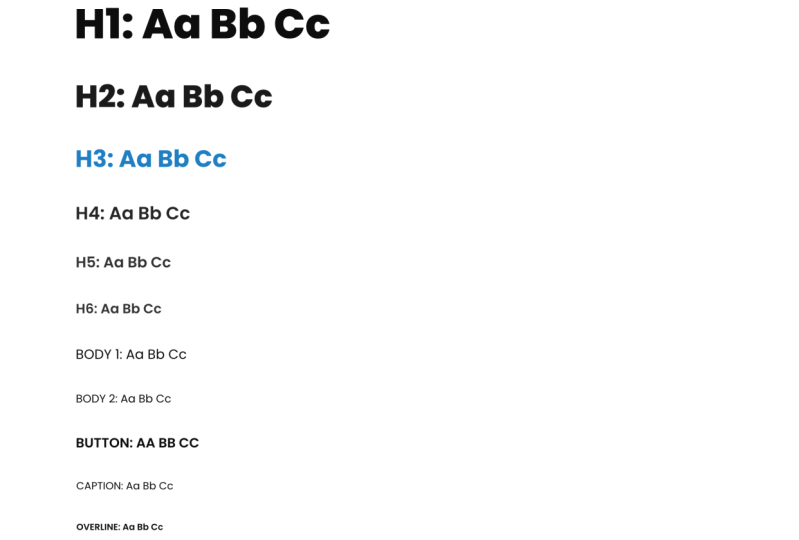
1. Introduction du cours: Les polices sont un élément crucial de chaque conception, car ce
sont elles qui
racontent l'histoire, guident l'utilisateur là où
il doit cliquer et où il doit aller
dans votre conception. Donc, choisir une bonne famille de polices et choisir une bonne famille de polices
pour les déchets est vraiment important et vraiment
une clé pour avoir un bon
et familles de polices, poids de police et
allons parler des différentes polices et familles de
polices. Quelle est la différence
entre eux ? Que sont les empattements et les sans empattement, différents poids de police
et comment les utiliser , les
différentes polices, échelles,
et comment les utiliser et créer votre propre bot pour choisir les
polices pour vos projets. Et enfin, comment associer des polices. Votre projet dépend de la complexité du projet
dans le sujet du projet, votre
projet de classe Skillshare consiste à créer une échelle de police à l'aide du
pour vous en tant que designer. Et cela profitera vraiment à vos utilisateurs, car cela
leur donnera plus de valeur. Ils vont
y rester plus longtemps parce que c'est une
expérience plus agréable pour eux. J'ai donc hâte de vous
voir dans ce cours et créons de
superbes combinaisons de polices.
2. Polices de polices VS: L'une des principales erreurs
que je vois de jeunes designers faire est d'appeler des polices, des polices caractères, ce qui
n'est pas vraiment vrai. Typeface est vraiment
une famille de polices. Et la police n'est qu'une variation au
sein de cette famille. Laissez-moi vous donner un bref exemple. Imaginez que vous utilisiez la police
Roboto par exemple. Et puis à l'intérieur de
l'autre fonte d'eau, vous avez Bolt, Regular,
Fine, Ultra Bold. Ce sont toutes des polices, mais le rapport lui-même est une police. La famille endettée est la principale
idée fausse des designers. Ils essaient de
pousser l'idée
que la police est primordiale
alors qu'elle ne l'est pas vraiment. Ce que vous pouvez avoir, c'est différents types de
variations de polices à l'intérieur de la même famille ou
une bouteille est vraiment un bon exemple car
vous avez Roboto regular, Roboto normal et puis vous avez quelque chose appelé roboto slab, qui est complètement une police de caractères, lignes
vraiment grasses, et il est
vraiment utilisé principalement pour l'impression, mais vous pouvez également l'utiliser dans
une sorte de conception Web audacieuse. Mais c'est là le
point essentiel. N'essayez pas de confondre polices
avec des familles de
polices, car les familles de
polices peuvent contenir plusieurs polices différentes. Et les polices ne sont que des variations au
sein de cette famille de polices. Comme je l'ai dit, il peut y avoir plusieurs polices
au sein d'une même famille. Alors gardez cela à l'esprit
et ne vous y trompez pas. Vous pouvez utiliser toute la famille ou police à l'intérieur de votre design, ou vous pouvez simplement utiliser
une variante telle que, disons dans cet exemple, Roboto regular ou Roboto bold. Nous allons y revenir dans quelques vidéos de ce cours. Mais je
voulais juste le souligner.
3. Types de polices: Souvent, lorsque j'
interviewe de jeunes designers
lorsque je leur parle, ils ne savent pas vraiment quelle est
la différence entre Serif et Sans Serif
en matière de police, c'est vraiment super simple. Et je suis allé de l'avant et j'ai trouvé
un très bon article. Je vais le lier dans le fichier de ressources de
la classe. Alors assurez-vous de le regarder et lire vous-même
car nous
n'allons pas l'approfondir trop
dans cette vidéo, mais je veux juste vous montrer
rapidement quelles sont les différences
entre les empattements, sans empattement, et lorsque
chacun d'entre eux est utilisé. Voici donc
cet article que j'ai
mentionné et qui provient d'Adobe.com, Creative Cloud Design Discover. Et je vais laisser
le lien vers cet article, comme je l'ai dit dans les fichiers de ressources de la
classe. Vous pouvez donc voir quelques
exemples ici. Peut-être que cela ne vous permet
pas de vous distinguer. Vous avez peut-être vu des polices comme celles-ci. Mais quelle est réellement
la différence entre Serif et Sans Serif ? Nous avons donc ici l'indice dans le nom et la principale
différence entre ces polices. Donc ces choses à la fin de
la lettre elle-même sont du surf. Et vous pouvez voir ici, nous n'avons pas
ce surf de sable, si je ne me trompe pas,
c'est français. Donc sans ces
empattements à la fin. C'est donc la principale différence entre les serfs et les serveurs d'envoi. Maintenant, quand vous pouvez les utiliser, vous pouvez voir quand
utiliser des polices avec empattement. Il va donc être
très détaillé savoir quand les utiliser
et comment les utiliser. Vous pouvez les voir en
version imprimée ici. Alors n'oubliez pas de consulter cet article pour
en savoir plus à ce sujet. Et bien sûr, vous pouvez en savoir plus sur le moment où les
trouver. Mais en un mot, quand utiliser des empattements et des capteurs, c'est vraiment très simple. Tout dépend du sujet de votre conception et
de
la direction de conception de
votre conception et de ce pour quoi
vous concevez. Ainsi, par exemple, si
vous concevez design de site Web
audacieux,
peut-être quelque chose de nouveau, quelque chose
pour la jeune génération, vous n'allez pas utiliser de
serveurs, qui sont les polices
avec ces éléments. À la fin de chaque lettre, vous allez utiliser des polices sans
empattement car les polices
Cera sont vraiment attribuées à quelque chose
d'ancien. Et si vous concevez pour quelque chose d'
ancien, par exemple, vous créez une sorte de site Web
vintage ou vous organisez une
sorte de salon de voitures anciennes peut-être ou quelque chose
qu'ils ont résolu. Ensuite, vous allez
utiliser les polices Serif, qui ont ces éléments à
la fin des lettres. Mais en
règle générale, si vous ne concevez pas pour
quelque chose de traditionnel, d'élégant, de vieux, vous allez utiliser ces polices sans empattement,
car elles sont polices plus modernes et
plus disponibles à l'utilisation, en
particulier dans la conception de sites Web, car elles fonctionnent en ligne et sont optimisées
pour le travail en ligne, pour la lisibilité, l'accessibilité, des polices plus modernes et
plus disponibles à l'utilisation, en
particulier dans la conception de sites Web,
car elles fonctionnent
en ligne et sont optimisées
pour le travail en ligne,
pour la lisibilité, l'accessibilité,
évolutivité, pour
toutes ces raisons, polices
sans empattement sont
bien meilleures à utiliser, en particulier dans la conception de sites Web. Mais comme je l'ai dit, vous pouvez toujours trouver des milliers de polices avec empattement
différentes si vous souhaitez les
utiliser dans votre
conception Web ou la conception de votre application. Tout
dépend de votre sujet, de ce pour
quoi vous concevez, de votre public cible, ce que vous
essayez de transmettre, du type d'émotion, type d'épanouissement avec
la police c'est à vous de choisir. Il suffit donc de garder ces éléments à l'esprit lorsque vous
concevez pour le Web.
4. Poids de police et comment les utiliser: Lorsque vous commencez à utiliser
une famille de polices, en fonction de la famille elle-même, vous verrez qu'elle contient de nombreuses polices
différentes, qui sont étiquetées avec des noms
différents tels que regular teen bold, extra bold, italic,
gras, italique et beaucoup, beaucoup d'autres, selon la famille de
polices elle-même. Ce sont des poids. Et comment utiliser ces poids
dans différents scénarios. C'est ce dont nous allons
parler dans cette vidéo. Et je vais vous montrer
un exemple et vous donner juste une idée de l'
endroit où les utiliser. Voici donc l'exemple, et je suis dans Adobe XD, s'agit du fichier de conception d'
un de mes cours précédents, et je l'utilise simplement comme
exemple juste pour vous montrer toutes
ces différentes
épaisseurs de police et comment utiliser pour mettre en valeur ce que vous
voulez montrer dans vos créations. Donc ce que nous avons ici
à l'intérieur de la section des héros, si je le sélectionne et que je viens juste ici sur le
côté droit. Alors laisse-moi juste choisir
celui-ci. On y va. Vous pouvez voir que le nom de la
police est Open. Sans, la taille est 24 et
le poids est régulier. Alors pourquoi est-ce régulier ? Eh bien, parce que je
voudrais juste que les gens voient ça en premier, qui est évidemment
plus grand, plus prononcé et de couleur différente. C'est ce qu'on appelle le point d'
attention parce que je veux d'abord
attirer leur attention sur ce texte blanc, parce que je voulais qu'ils
lisent ce texte en premier. Par conséquent, je
veux qu'il soit
différent de ce
texte en haut
et en bas pendant
qu'ils sont ici au centre en train
de lire que cette
héroïne est un hôtel-boutique. Je veux qu'il voie qu'il y a un autre texte en haut
et en bas. Ensuite, j'ai envie de les lire. Je veux qu'ils le lisent
parce qu'ils sont là. Donc, si je lance rapidement
le prototype ici, vous pouvez voir à quoi il ressemble. Alors me voilà dans la section des héros et tout ce qu'ils peuvent voir c'est ça. Votre regard est donc naturellement attiré vers le
milieu de cette page, vers le milieu de cette image. Et vous pouvez lire que cette héroïne est boutique-hôtel après avoir été endetté. Vous pouvez voir tout ce qu'il
y a d'autres textes là-bas. Bienvenue au
boutique hôtel Helen's. OK, chez toi, loin de chez toi. C'est donc le poids de la police. Voilà comment les utiliser. Et vous remarquerez que
cette police est différente. Vous pouvez voir que c'est du surf, comme nous l'avons mentionné dans
une précédente vidéo. Alors pourquoi est-ce ? Parce que l'image de marque de cet hôtel et de ce
design l'exige vraiment. Et c'est pourquoi j'ai opté
pour ce genre de look. Donc si je choisis cela, vous pouvez voir qu'il s'appelle
Playfair display 70, qui est la taille de la police, beaucoup plus grande dans ce cas. Parce que non pas pour mentionner, encore une fois, toutes ces choses
que j'ai mentionnées, mais pour attirer l'attention là-dessus. Et puis vous pouvez voir le gras froid, italique est le poids. C'est Italica. C'est donc un peu penché vers la droite
et c'est audacieux. Elle est plus prononcée
qu'en police normale. C'est ainsi que vous pouvez équilibrer poids de
vos polices dans
de nombreux exemples différents. Et si nous faisons défiler un peu vers le bas, vous pouvez voir encore une fois, voici cette même police maintenant
dans une couleur différente pour obtenir le contraste entre fond
blanc
et la police elle-même. Et vous pouvez voir votre
maison loin de chez vous. Donc, encore une fois, nous
revenons peut-être à ce slogan. Ensuite, vous pouvez voir quelque chose de
vraiment intéressant ici. Donc si je sélectionne celui-ci, vous pouvez voir qu'il s'agit d'un boulon
Open Sans 24. Et si je sélectionne celui-ci, Open Sans 24 regular. Et vous pouvez voir
simplement en sélectionnant boulon et régulier et
en
choisissant une couleur différente, je pointe leur direction et
leur attention dans une direction différente. Dans cet exemple, vous pouvez le voir, j'ai eu envie de lire ce sous-titre parce que
c'est vraiment important. Je veux que leur esprit attentif à
ces trois choses. Donc, les lits king size, la
nourriture, y compris
l'accès à la plage, car ce sont arguments de
vente clés
vraiment importants pour ce site Web en particulier afin d'
attirer de nouveaux visiteurs. Et puis s'ils le
souhaitent, bien sûr, ils peuvent lire le texte en dessous. C'est pourquoi celui-ci est
audacieux et celui-ci est régulier. Celui-ci a une couleur légèrement
plus foncée que
celle-ci parce que je
veux que ses yeux
soient d' abord attirés par ce texte. Même histoire avec ça
et avec ça ici. Si vous faites défiler un peu maintenant, nous pouvons voir les mêmes
textes ici. boutique
hôtel Headwinds est très bien. Et voici une
citation d'un de nos anciens clients sur ce
site ou un témoignage, vous pouvez voir Jenny de Londres, mais celui-ci est beaucoup
plus prononcé. C'est beaucoup plus grand. Donc, si je le sélectionne
et que je viens juste ici, vous pouvez voir que c'est
Open Sans 36 italique. Et il a cette
couleur plus foncée que celle-ci, qui est irrégulière Open Sans 24. Encore une fois, je veux
qu'ils lisent d'
abord la citation , puis qu'ils voient de qui
est la citation. Le nom dans ce cas n'a pas
vraiment d'importance. Vous pouvez vous en débarrasser
pour les séquences de mise en page. Peu importe ce qui compte c'est leur expérience
avec cet hôtel, car le prochain client que
vous essayez d'acquérir pour votre hôtel
voudra d'abord vivre cette expérience. fichais vraiment, est-ce que c'est Jenny, utilise-le, Mark, est-ce qui que ce soit ? Ils ne s'en
soucient pas vraiment, ils se
soucient vraiment de l'expérience. Ensuite, vous pouvez
voir le contraste dessous avec le bouton
Livre maintenant, qui est bleu et
contient du texte blanc. Encore une fois, pour des raisons de
contraste, si nous faisons défiler un peu vers le bas, vous pouvez le voir
tout au long de ce design. Et pas seulement ce design, mais chaque
design que je crée. Parce que je
pense toujours à ces choses-là. Qu'est-ce qui est le plus important ? Qu'est-ce qui est le moins important ? Qu'est-ce que les gens
vont voir en premier ? Et comment puis-je accentuer cela avec mes polices et mes épaisseurs de police ? Vous pouvez le voir ici. Donc, pour les noms de la pièce, police est beaucoup plus grande que
toutes celles ci-dessous. Et vous pouvez le voir avec
les fonctionnalités, oui et non. Bien entendu, nous choisissons ensuite différentes couleurs pour montrer
quelles fonctionnalités sont disponibles celles
qui ne le sont pas. Et puis nous avons encore
une fois le style
différent avec le lien ci-dessous. Pour en savoir plus, ils peuvent cliquer sur
ce lien, c'est différent. Alors quand le, comment va,
ils verront le changement. Vous devez donc réfléchir à
toutes ces choses. Ici. Vous pouvez voir les fonctionnalités. Nous avons donc une piscine privée, nous avons un beau jardin, nous avons un parking privé. Tout cela est super facile
à lire dans un but précis. C'est pourquoi j'ai choisi cette
police, qui est beaucoup plus grande, qui est un peu différente,
qui est boulder, a une couleur plus foncée que
la police en dessous. Une fois de plus, j'utilisais
Open Sans comme police principale. Celui-ci juste
ici, et Playfair affiche cette grosse police en gras. Encore une fois, si nous faisons
défiler un peu vers le bas, vous pouvez voir cela
se reproduire. Alors visitez Délos,
qui est le titre, et voici le texte. Donc si je ne
veux pas lire ce texte,
tout ce que je peux voir et tout ce que j'ai besoin de savoir, c'
est de visiter Délos. Il y a donc quelque chose
à faire lors des expositions. Et si nous faisons défiler la page un peu vers le bas, encore
une fois, réservez
votre séjour chez nous. Cela
les invite donc vraiment à réserver leur
séjour dans cet endroit. Et encore une fois, vous pouvez voir
ce contraste ici même avec le fond
blanc et ce texte gris foncé. Et le dernier exemple est l'
inscription à des bulletins d'information. C'est donc vraiment vous appeler
à l'action, à passer à l'action. Et puis voici ce que vous voyez. Tout d'abord, inscrivez-vous à une newsletter. C'est ce que vous voyez ensuite, et c'est
encore une fois dans un but parce que je veux
prononcer ça, inscrivez-vous à une
newsletter parce que c'est l'action que je
veux qu'il entreprenne. Et puis une fois que j'ai leur attention en m'
inscrivant à la newsletter, inscrivez-vous et recevez des nouvelles
et des mises à jour et blah, blah. C'est vraiment secondaire
parce que je veux qu'ils restent sur cette partie de la
page le plus longtemps possible. C'est ainsi que vous pouvez utiliser des
polices, des modes de police et différentes couleurs, et peut-être même différentes familles de
polices pour accentuer ce que vous souhaitez que vos
utilisateurs voient sur votre page. Vous pouvez l'explorer beaucoup plus
en détail. Et en fonction de votre
palette de couleurs pour votre projet, cela peut être vraiment encore plus complexe ou même
plus simple que l'exemple que
je viens de vous montrer, qui ne contient que
quelques couleurs.
5. Choisir les polices: Lorsqu'il s'agit de choisir des
polices pour votre projet, il y a deux considérations
principales à prendre en compte. Vous devez avoir des polices existantes et le thème principal
du projet, les polices existantes sont
évidemment les polices que votre client
utilisait auparavant. Ensuite, vous pouvez jeter un
œil à ces polices. Voyez toute la famille de polices, voyez ce qu'elle contient et réfléchissez peut-être à la manière dont vous pouvez l'accentuer
un peu plus. Ce dont nous avons parlé dans une
précédente vidéo de ce cours. Comment pouvez-vous les utiliser un
peu différemment pour montrer certaines caractéristiques principales
du produit ou d'un service proposé par votre
client. Ensuite, vous pouvez regarder
les couleurs, voir comment la famille de polices précédemment utilisée avec
ces différentes couleurs. Peut-être que si vous en avez
la capacité, vous pouvez
peut-être changer
ces couleurs. Peut-être que vous pouvez inclure
des couleurs plus
foncées, des couleurs plus claires. Peut-être que vous pouvez ajouter des nuances de ces différentes
couleurs qu'ils utilisent
déjà ou introduire nouvelles couleurs entièrement
dans le projet pour donner plus de vie et plus de talent au projet.
sur lequel tu travailles. L'autre méthode consiste à
utiliser de nouvelles polices. Et lorsque vous
choisissez de nouveaux fonds, faites
attention à ce que j'ai déjà mentionné dans l'une
des vidéos précédentes. Apprécié du projet lui-même. Évidemment, vous n'
allez pas utiliser ces polices
audacieuses, lumineuses et loufoques. Si vous créez un
site Web pour une banque, peut-être parce que la banque essaie transmettre un sentiment de confiance, de sécurité, de stabilité. Je ne connais pas la noblesse
dans certains cas. Vous devez donc y prêter
attention. Quel est l'objet de votre projet ? Qu'est-ce qu'il a essayé
de transmettre aux utilisateurs eux-mêmes ? faut donc
utiliser ces polices qui vont bien correspondre
à l'équipe du projet. Bien sûr, si le
projet est bon, disons que vous créez un site Web pour
une société de
bandes dessinées ou un magasin de jouets
ou tout type de contenu
lié aux enfants tel que jeux, des peluches ou des meubles, peu importe ce que ça a à voir avec les enfants. Mais même avec les enfants, il y a encore des limites
quant au moment où vous pouvez
utiliser certaines polices façon dont vous pouvez les utiliser. Parce que l'héritabilité
est vraiment la clé, en
particulier en ligne,
vous voulez vous
assurer que vos polices sont
lisibles en fin de compte, quel que soit votre public
cible, peu
importe si c'est
sérieux ou ludique, s'il est coloré,
tout en monochrome, vous voulez quand même savoir
s'il est lisible ou non. Et pour ce faire, vous pouvez le
tester sur
différents appareils. Lorsque vous créez un
site Web, par exemple, vous devez le
tester sur de grands écrans
tels que les écrans de bureau
et les écrans d'ordinateurs portables, mais vous devez également vous
assurer qu'il fonctionne bien et qu'il est lisible sur
des écrans plus petits tels que Forms. Si vous utilisez
quelque chose comme Webflow, c'est très facile à faire. Créez simplement une page
réactive à partir de votre conception et
envoyez-vous simplement le lien, peut-être envoyer ce lien
à quelqu'un qui est plus âgé, au nouveau peut-être, et
voyez s'il peut lire facilement si la
couleur le contraste est bon, si les épaisseurs de police sont bonnes, si votre rythme de couleur est bon. Ils peuvent donc vraiment le lire. Ils peuvent vraiment le comprendre et voir
ce que vous essayez de transmettre dans cette page en
particulier. Assurez-vous donc de toujours tester, toujours
penser à l'avance. qui parlez-vous ? À qui parles-tu ? Quel est votre public principal ? Et la police est-elle lisible en utilisant ces couleurs sur ce
fond ?
6. Associer des polices: Parfois, dans certains exemples, vous souhaitez utiliser
différentes familles de polices, comme dans l'exemple que je vous ai montré
précédemment
avec ce site de voyage. Peut-être souhaitez-vous afficher une section
différente de cette page ou une application mobile
utilisant une certaine famille de polices. Et puis une autre section, peut-être voulez-vous qu'ils aient l'
impression de
lire un article. Par conséquent, vous n'allez pas
utiliser une police folle et loufoque. Vous voulez simplement résumer une vieille police
ordinaire, vraiment lisible, compréhensible et super facile à voir et à lire
pour eux. Par conséquent, vous
devez connaître couplage de
polices et
comment associer des fonds ? Eh bien, il existe
différents outils en ligne qui peuvent vous aider. Et je vais en montrer quelques-unes
dans cette vidéo en particulier. Nous voici donc avec la première de ces variantes de
type froid. Et j'ai déjà créé
une vidéo YouTube. Je vais le relier dans les ressources
de la classe. Vous pouvez simplement cliquer et regarder cette vidéo complète dans laquelle j' explique tous ces
différents outils. Mais je vais juste
vous donner un bref aperçu. Dans cette vidéo en particulier, vous avez de l'inspiration
et des guides qui vous guident sur la façon de coupler
ces différentes polices. Encore une fois, tout dépend de
ce qui a déjà été mentionné à quelques reprises dans cette vidéo, du sujet de votre projet et du public auquel vous
essayez de vous adresser. Par conséquent, vous
n'allez pas utiliser des polices loufoques comme cela ne cesse de le
mentionner aux banquiers, par
exemple, ou à un public
sérieux. Mais vous pouvez aller dans l'autre sens
avec les enfants et utiliser des couleurs plus ludiques et
des polices plus ludiques. inspiration de type est donc le premier site Web et vous pouvez choisir de nombreux styles
différents. Vous pouvez voir Open Sans et de la crème. Certains textes sont les
polices utilisées ici. Voici les couleurs. Vous pouvez choisir
différentes couleurs parmi. Ici vous pouvez choisir les polices de
titre, vous pouvez choisir les polices de corps. La police de titre est
celle qui se trouve juste en haut, qui est utilisée pour les
en-têtes ou pour les titres. Et la police du corps est
celle-ci juste ici, qui est utilisée essentiellement
pour les paragraphes et pour tout le contenu
qui contient plus de texte. Et il est davantage
destiné à des tarifs plus longs. Fondamentalement,
les titres sont plus de glandes, mais vous pouvez également
les lire très rapidement. Mais les paragraphes, vous
pouvez vraiment avoir à passer votre temps à les lire. Et c'est le
point principal ici. Avec les paragraphes, vous pouvez explorer différentes
polices et épaisseurs de police. Mais avec les paragraphes,
vous voulez vous
assurer que votre police est lisible, que la couleur a un beau contraste avec l'
arrière-plan. Et ce n'est vraiment pas
trop
fatiguant pour vos yeux de passer plus de
temps à lire cet article, surtout
s'il y a un article plus long, si vous créez un site Web
pour , par exemple,
extrêmement important. C'est le
problème clé que vous devez abord et immédiatement
aborder
dans ce projet en particulier, car l'intérêt
d'un site d'actualités est les gens passent beaucoup de
temps à lire ces articles. Par conséquent, vous voulez avoir une bonne police qui
soit vraiment lisible. Et ces titres
qui sont vraiment
consultables parce que
vous ne voulez pas ils ressortent trop, en
particulier dans ce
type de sites Web, parce que vous voulez qu'
ils continuent à
passer à la lecture ces
articles ci-dessous. Alors explorez ce site Web. Comme je l'ai dit, je vais
pointer du doigt la vidéo que j'ai déjà créée sur
ma chaîne
YouTube à ce sujet. Et j'explique cela plus
en détail. Et je vais laisser
les liens dans cette vidéo, alors jetez-y un œil. La paire de polices en est une autre. Vous pouvez donc voir ici que
nous avons une plaque à empattement sensoriel. Vous pouvez donc voir que c'est une sorte d' écriture manuscrite
d'affichage monospace. Il existe donc un tas de styles de police
différents parmi
lesquels vous pouvez choisir. Et vous pouvez voir toutes
ces polices importantes et la police principale. Vous pouvez voir les combinaisons
ici, vous pouvez voir plus de paires de polices. Choisissons donc les polices
d'affichage et il
va vous montrer toutes
ces polices d'affichage. Vous pouvez les découvrir. Ensuite, nous avons ceci, qui est des appariements de polices,
point py people.com. Vous pouvez sélectionner une
famille de polices ici. Et après cela,
vous pouvez choisir différents styles de
textes et le style. Donc c'est régulier,
c'est en gras, cette dalle de textes secondaires, qui est ce texte
de paragraphe que nous venons de mentionner. Ensuite, il
vous donnera des appariements disponibles. Et enfin, Font Joy, qui est super,
super simple à utiliser. Nous avons donc Generate
et cela va
générer une paire de
polices différente. Vous pouvez choisir plus de
contraste ou vous pouvez choisir plus de similitude
ou de contraste équilibré. Vous pouvez passer du noir au
blanc pour voir à quoi cela
va ressembler. Surtout si vous concevez un mode sombre sur votre
site Web ou votre application, vous pouvez voir les appariements de polices
et
différentes tailles de texte, différents poids, etc. Nous voici donc Montserrat, qui est celui-ci juste ici. Ici, nous avons cette
police Varney simulée, qui est celle-ci juste ici. Ainsi, vous pouvez voir H1, H2 et le paragraphe ou le titre d'un titre, deux paragraphes ou un
titre principal , un sous-titre et un paragraphe. Sanchez est le texte
du paragraphe lui-même. Vous pouvez donc cliquer sur. Cela
vous amènera à Google Fonts, ce que cette police
Sanchez est composée de quatre. Ensuite, je peux cliquer
ici et je peux choisir, je ne sais pas, peut-être
celui-ci juste pour voir à
quoi il ressemble. Si je n'aime pas ça, ça va aller de l'avant
et changer ça. Disons que je n'
aime pas vraiment ceux-ci ou celui-ci. Peut-être que je peux opter
pour quelque chose d'un peu plus brillant comme celui-ci. Je peux le verrouiller ici. Et ça va
verrouiller ce Montserrat. Je n'aime pas vraiment celui-ci, donc je peux aller de l'avant
et générer plus. Vous pouvez voir que
Montserrat est verrouillée, peut-être que j'aime bien celui-ci, mais je n'aime pas celui-ci. Nous pouvons aller droit au but. Vous pouvez toujours faire défiler la page vers le bas. Et à la fin, lorsque vous trouverez la
combinaison de polices parfaite que
vous souhaitez utiliser, comme je l'ai mentionné, vous
pouvez cliquer ici. Cela va
vous mener à Google Fonts. Assurez-vous de télécharger la famille de police
Montserrat in Montserrat,
puis de les découper. Et le pylône Quinn, dans cet exemple
particulier, s'
assure de tous les télécharger, les
installer sur une machine. Vous avez donc toutes ces
différentes épaisseurs de police, comme je l'ai mentionné, du gras normal, et bien plus encore. Tu y vas. Voilà à quel point il
est facile de faire une paire de polices. Faites
attention à qui suit, au contraste, à la lisibilité
et au sujet de ce que vous concevez
en premier lieu. Vous avez tout réglé. Ensuite, ce
sera vraiment facile à concevoir et à peine
facile à tester. Et en ce qui concerne les tests, assurez-vous de toujours les
tester auprès de votre public, surtout si vous y
avez accès. Ainsi, par exemple, si vous
concevez pour des enfants, vous pouvez
peut-être avoir
accès aux enfants et voir comment ils interagissent
avec le prototype, comment ils interagissent avec le site Web, avec
application mobile. Est-il facile pour eux de
comprendre où ils
doivent cliquer plutôt que de tomber sur ces différents
éléments de votre conception ? Peut-être que quelque chose leur attire
trop l'attention. Ou si vous travaillez
avec un public plus âgé, peut-être comme je n'arrête pas de
mentionner les banques, peut-être avez-vous accès
aux personnes qui
travaillent dans la banque. Si vous travaillez pour une banque
dans ce cas précis, vous pouvez
peut-être le tester avec
elle,
lui confier une tâche concrète, voir à quel point il
est facile pour elle de trouver cette tâche, à quel point c'est facile pour pour naviguer dans
votre application et voir à quel point il est
facile
pour eux de lire le texte vous essayez d'afficher sur
cette page en particulier.
7. Échelle de police: Lorsque vous concevez pour
le Web ou pour des applications mobiles, vous souhaitez avoir une mise à l'
échelle
composée de vos tailles
et épaisseurs de police. Et cela peut être réalisé
avec une échelle de police. Vous pouvez créer une échelle de police, il sera
donc beaucoup plus facile pour
les développeurs de
comprendre plus tard quel type de taille de
police est destiné à quoi, et c'est ce que vous pouvez
inclure dans votre guide de style, juste pour les afficher à
côté de votre les couleurs , ainsi que vos images, vos
styles et bien plus encore. Dans cette vidéo, je
vais donc vous montrer
comment créer une échelle de police
simple. Vous n'êtes pas obligé
d'utiliser cette approche. Vous pouvez trouver d'autres
approches en ligne. Il existe littéralement des dizaines d'approches différentes en ligne. Découvrez celui qui fonctionne pour vous, votre projet et vos objectifs de
mise à l'échelle. Alors commençons. Nous voici donc dans Adobe XD et
je vais simplement vous montrer
comment créer une
échelle de police rapide à l'aide d'Adobe XD. Si vous utilisez Figma Photoshop, tout ce que vous pouvez y
créer. Mais pour cela, je vais utiliser x
D parce que je l'
aime vraiment et je l'utilise
tous les jours. Je vais donc cliquer sur T pour
créer H1, par exemple. Alors ce que je vais utiliser, c'est, disons une bouteille comme ça. Au lieu de la normale,
je vais opter
pour , disons, du noir. Et je vais opter pour
une taille de 80. Vraiment énorme. Et ça va être mon H1. Peut-être, peut-être même plus, peut-être 88, quelque chose comme ça. On y va. Ensuite, je vais appuyer sur
Control D ou Command D, et baisser ce chiffre à
quelque chose comme 64. Tu y vas. Au lieu du noir, je
vais choisir Bolt. Et au lieu de H1, je vais l'appeler H2. Ce qui est créé
ici est donc une distinction claire
entre Heather. Bruyère. Heather One est quelque chose
que je vais
utiliser dans mes
images de héros, par exemple, au centre du design lui-même, au centre de
ces images de héros. Contrairement à l'exemple que
je vous ai montré précédemment. Mais celui-ci est juste
plus accentué, plus grand, plus audacieux,
noir dans ce cas, mais celui-ci est audacieux parce que
je veux peut-être l'
utiliser comme titre de mes sections peut-être ou
quelque chose comme ça. Par conséquent, il est audacieux et
non noir et c'est 6488. Donc, si nous descendons
un peu plus loin, vous pouvez créer un
H3 dans ce cas. Et au lieu de 64, nous pouvons
peut-être en utiliser
48 pour ce cas. Et au lieu de Bolt, en fait non,
restons audacieux pour ça. Ensuite, si nous descendons un peu, nous pouvons créer quelque chose comme H4. Et au lieu de 48, nous pouvons
peut-être opter pour
40, dans ce cas n. Utilisons une régulière cette fois. Vous pouvez donc clairement faire la
distinction entre ces deux éléments. Donc si nous descendons un peu H5, et dans ce cas, peut-être que nous pouvons utiliser quelque chose, je ne sais pas, 24. Peut-être qu'on y va. Peut-être pouvons-nous utiliser
cela comme texte de paragraphe ou quelques exemples ou
quelque chose comme ça, quelque chose qui est un peu
plus petit et H6, allons-y, je ne sais pas, 16 peut-être que dans mes cas, je ne veux vraiment pas y
aller au-delà de 16. Nous avons donc H1, H2, H3, H4, H5 et H6. Peut-être pouvez-vous renommer ce H6 et l'appeler textes de
paragraphe. Peut-être pouvez-vous montrer quelque chose comme ça à vos développeurs, voir ce qu'ils en pensent. Et ce que vous pouvez également faire, c'est appuyer une fois de plus sur Ctrl D sur chacun
d'eux et taper l'alphabet. Donc a, a, B, B, B ,
C, C, D , D,
E, etc. Vous pouvez donc taper l'alphabet
entier et afficher le poids de la police et la taille de la police dans cet exemple particulier
sur l'alphabet, ou quelque chose d'autre
que vous pouvez faire est utiliser quelque chose comme Je ne sais pas, le
texte de Lorem Ipsum ou quelque chose comme ça. Je n'ai pas le
raccourci clavier ici, et le plug-in n'est pas
installé ici. Alors allons-y avec ça. Alors Lorem Ipsum ROC s'est rencontré, peut-être pourrais-je copier ce texte et ensuite je pourrai faire de
même avec celui-ci. Il suffit de le coller. Et ce que cela
va vous permettre de
faire , c'est de montrer à votre client et à vos développeurs
à quoi ressemblera un texte
particulier dans des cas d'utilisation particuliers. Disons donc que j'ai volontairement commencé avec
cette couleur particulière. Et la raison pour laquelle j'ai choisi de le faire c'est simplement pour vous montrer
les principales différences entre ces textes. Mais dans ce cas précis, ce que je ferais exprès, c'est que j'
irais rapidement de l'avant et que je changerais cette couleur pour quelque chose de
beaucoup, beaucoup plus sombre. Et peut-être l'enregistrer
ici en tant qu'échantillon de couleur. Ou je peux continuer et modifier mes couleurs
ici. Alors ce que je peux faire, c'est. Débarrassez-vous de celui-ci. Peut-être que je peux aller de l'avant
et choisir la même couleur, mais aller quelques pas
vers quelque chose comme ça, puis choisir
une couleur différente. Et ce que vous pouvez faire, c'est donner nom de
vos échantillons immédiatement. Donc celui-ci est H2, couleur. Tu y vas. Celui-ci est H1. Et peut-être que nous pouvons
aller encore plus loin. Désolée, voyons
si c'est un H2. Je peux donc revenir en arrière et utiliser le H12 puis passer à la vitesse supérieure,
quelque chose comme ça. Gardez-le ici, enregistrez-le ici, appelez cet âge de trois ans. On y va. Et enfin,
peut-être que je voudrais
opter pour quelque chose d'encore plus brillant. Pour celui-ci, peut-être, peut-être pas, mais
c'est vraiment à vous de décider. Peut-être quelque chose comme ça. Tu y vas. Et je peux lui donner le nom de H4. Dans ce cas particulier, vous pouvez voir qu'ils sont
vraiment similaires. Mais il y a l'
intérêt de cette vidéo, mais vos clients
ont peut-être la couleur principale, disons que le bleu est
leur couleur principale. Donc, dans ce cas, nous pouvons opter pour quelque chose
comme trois C6 FF peut-être. bleu très vif
et fort, c'est
peut-être leur couleur principale. Alors, comment intégrer
cette couleur dans votre design ? De toute évidence, vous n'
allez pas l'utiliser pour cela. C'est vraiment pour les sections de
héros et tout ça,
ce que j'ai déjà mentionné. Peut-être allez-vous l'
utiliser pour chacun des trois. Donc trois est C6, F, F. Et comme vous pouvez le voir tout de suite, cela semble beaucoup mieux
dans cet exemple que dans cet
exemple. Pourquoi est-ce que c'est ? Parce que si vous l'utilisez pour la plus grande taille de texte que
vous avez dans votre conception, cela volera simplement l' attention
de
l'utilisateur sur tout le reste. Ce n'est pas quelque chose
que tu veux. Le texte est vraiment là
pour expliquer les choses afin de guider vos utilisateurs vers
ce qu'ils doivent faire ensuite, et pour vraiment les aider atteindre l'objectif leur visite sur votre
site Web ou votre application mobile en particulier. Dans ce cas, j'utiliserais couleur pour le texte,
quelque chose comme ceci. Et je ne l'utiliserais pas pour les textes de
paragraphes car, comme
je l'ai mentionné précédemment, vous voulez que vos paragraphes
soient lisibles. Vous voulez qu'ils soient
facilement compréhensibles et que vos
utilisateurs puissent
naviguer facilement
tout au long de votre conception. Une dernière chose
que j'ai oublié de faire est de sauvegarder cette couleur. Nous l'avons déjà. Tu y vas. Donc H5, je veux le sauver. On y va. H5. Et nous allons utiliser la même couleur pour
le paragraphe lui-même. Et une dernière chose que
je veux faire est de sélectionner toutes mes tailles de police, d'accéder directement aux
styles de caractères et de cliquer là. Vous pouvez donc voir qu'il va les assortir,
quelque chose comme ça. Mais ce que je peux faire, c'est aller sur
Control ou Command Z. Cliquez ici pour enregistrer
celui-ci pour qu'il soit le premier. Et puis comme ça, et il suffit de monter et de monter. On y va. Et bien sûr, vous
pouvez les renommer. Vous pouvez venir
ici et taper H1. Et vous pouvez le faire avec
tous ces autres. Donc H2, H3, et ainsi de
suite et ainsi de suite. Je ne vais pas trop
t'embêter avec ça. Mais le but
ici est de les renommer. Comme je l'ai dit, il est beaucoup plus facile pour les développeurs de comprendre
plus tard ce que vous
essayez de transmettre si vous n'allez pas développer
ce design vous-même. Alors allons-y. C'est comme ça que c'est super
facile à utiliser. Et vous pouvez voir si vous vous trompez comme je l'ai fait tout à l'
heure, vous pouvez simplement voir les arcades
en H1 sélectionnées ici. Ou si vous avez accidentellement
changé la couleur, vous pouvez continuer et voir, d'accord, c'est un clic H1 juste là, et il va utiliser la
couleur correspondante. Vous pouvez donc voir à quel point c'est
super simple. Et je vais vous
fournir ce fichier, que je viens de vous montrer en
tant que fichier d'entraînement pour vous
afin que vous puissiez le tester. Fouillez, exploitez
pour vous-même, peut-être en jouant avec ces différentes couleurs
qui viennent de vous être montrées, ou peut-être des
familles de polices entièrement différentes. Nous utilisons donc Roboto dans
ce cas particulier, peut-être voulez-vous
utiliser quelque chose avec
une surface à l'intérieur, comme la police d'affichage
Playfair, que j'ai mentionnée précédemment, ou voulez-vous être
encore plus audacieux que Roboto ? Tu peux le faire correctement. Là-bas. On y va. Ce sont les échelles de police, et c'est ainsi que vous pouvez les utiliser. Comme je l'ai dit, vous allez
avoir ce fichier d'entraînement, assurez-vous de l'exploiter, assurez-vous de jouer pour
obtenir un résultat parfait. Ou si vous n'aimez pas cette approche de
huit pixels,
comme je l'ai dit au
début de cette vidéo, vous avez un tas de ces exemples
différents en ligne. Assurez-vous de les explorer
par vous-même et de voir ce qui
fonctionne le mieux pour vous.
8. Votre projet de cours: Votre projet de classe consiste à
créer votre propre échelle de police, à l'
enregistrer sous forme d'image et à la télécharger dans
vos projets de classe. Ainsi, moi et
tous les autres participants
au cours pouvons voir
ce que vous avez créé. Vous pouvez donc utiliser ce modèle que je vais fournir dans les documents de la
classe. Vous pouvez le télécharger et vous
amuser par vous-même. Assurez-vous d'utiliser
différentes polices, familles de
polices de
différentes couleurs juste pour obtenir vos
différents résultats. Et vous pouvez explorer
avec deux polices de caractères. Je ne recommande pas d'
aller plus loin parce que je n'aime pas vraiment quand les gens
utilisent plus de deux polices, je ne pense pas vraiment que
ce soit nécessaire, mais vous pouvez en faire ce que
vous voulez, ou vous pouvez même ajouter d'autres tailles. Vous pouvez jouer
avec différentes tailles et vous pouvez regarder
ce que j'ai créé ici avec toutes
ces couleurs
et styles de personnages différents, assurez-vous de
jouer avec eux pour obtenir un résultat parfait. Et puis, comme je l'ai dit,
téléchargez-le dans vos projets de classe. J'ai hâte de voir
ce que vous
allez créer
et je suis impatiente de
voir comment vous allez adapter ce modèle que j'ai
créé dans Adobe XD.
9. Conclusion: Alors voilà,
c'est tout pour ce cours. J'espère vraiment que vous avez
mieux compris les familles de polices,
les polices, les différents poids de
police, comment et quand les utiliser, ainsi que ce que Sarah
est pour une personne sensible et quand utiliser ceux-ci, ainsi que, enfin, qu'est-ce qu'une échelle de police
et comment l'utiliser. J'espère vraiment que ce cours vous
a plu. Assurez-vous de consulter le PDF avec toutes les ressources
que j'ai mentionnées. N'oubliez pas de
consulter le fichier d'exercices pratiques et de voir à quoi il ressemble. Fouillez et
jouez pour vous-même. Merci beaucoup d'avoir
regardé ce cours. Si vous voulez vous assurer de
consulter mes autres cours, en
particulier dans mes masterclasses, qui
durent plus de 20 heures, entrez dans de nombreux détails